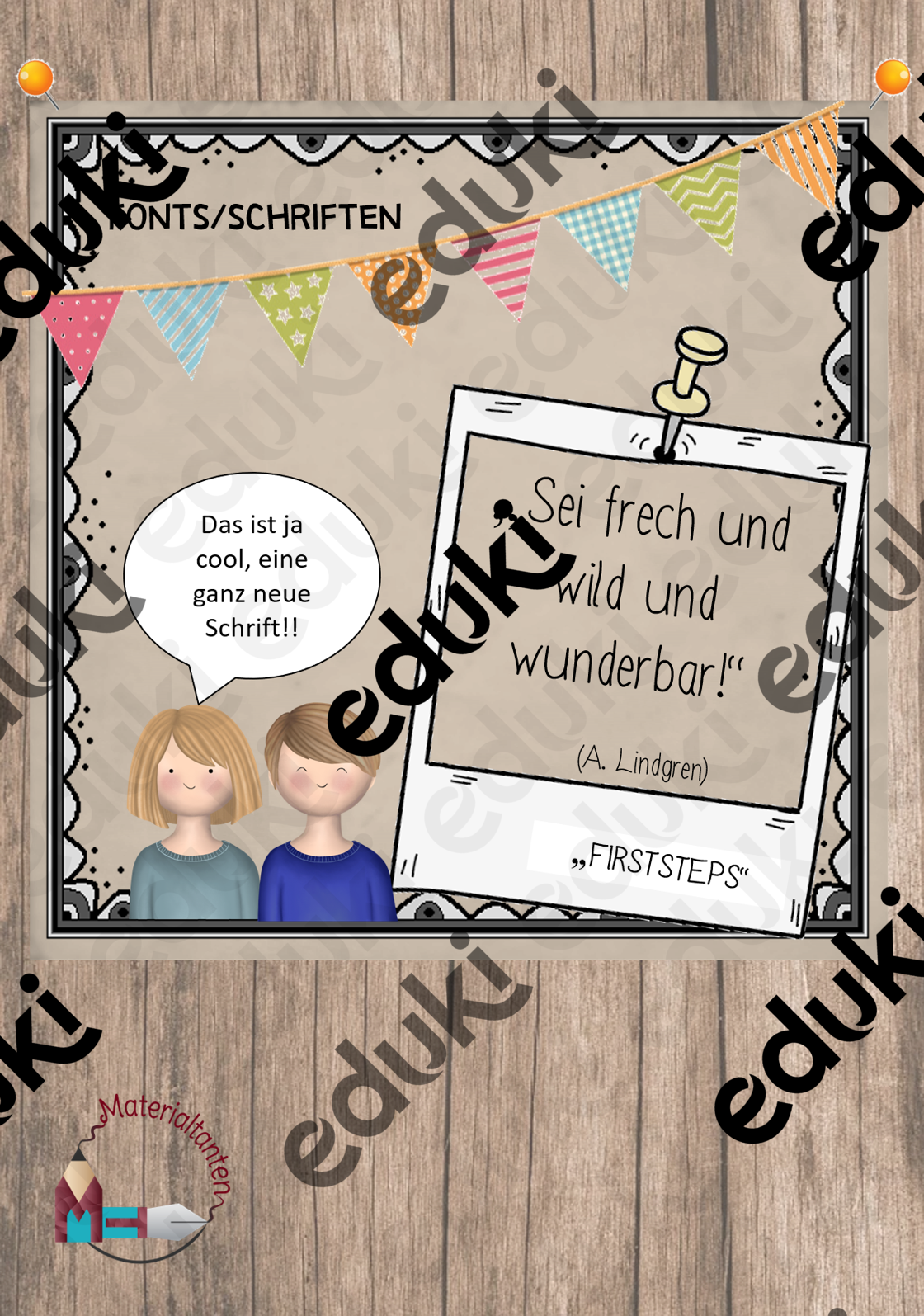
selbst erstellte Schriftarten - FirstStep2(1) Font/Schrift - Materialtanten - Deckblatt
Eine individuelle Note für deine Dokumente und Schriftstücke. Handschriftenähnlich und trotzdem im Computer verfügbar!
FirstStep2(1) Font/Schrift